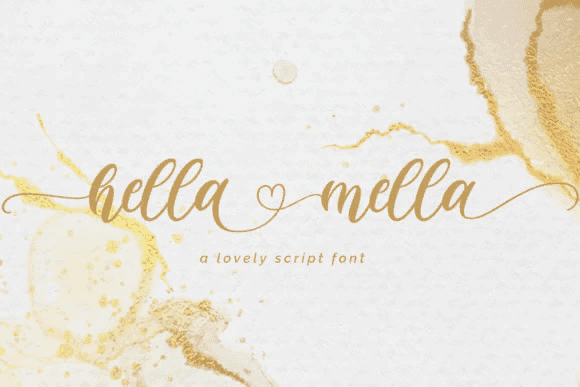
Название: Hella Mella Font
Hella Mella - это прекрасный шрифт. Влюбитесь в его аутентичность и используйте его для создания великолепных свадебных приглашений, красивых канцелярских принадлежностей, привлекательных постов в социальных сетях и милых поздравительных открыток. Этот шрифт закодирован в PUA, что означает, что вы можете легко получить доступ ко всем глифам и штрихам! Он имеет изменяющуюся базовую линию, плавные линии, великолепные глифы и потрясающие чередования.